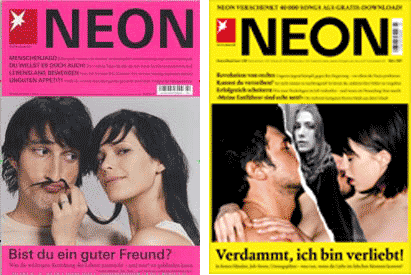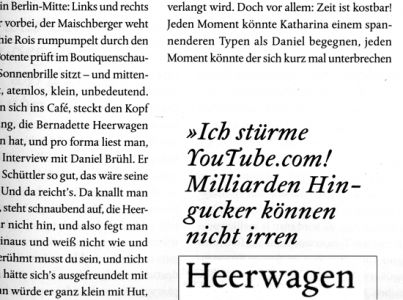
NEON verabschiedet sich von Univers
Das Blatt ist noch keine drei Jahre am Markt und gönnt sich schon eine neues Gesicht. Der Titelschriftzug hat sich in den Proportionen den Kapitälchen genähert, was ich gar nicht schlecht finde. Die Univers ist verschwunden für eine nette Antiqua, die ich leider nicht kenne. Schade um die Univers. Thats life.
der NEON-schriftzug schaut besser aus als vorher.
die positionierung des EAN-codes find ich allerdings
zweifelhaft ...
ich mache morgen mal einen bildschirmschuss. hab die neon gerade nicht im Büro. ist aber nicht die dolly.
Ja, der Schriftzug ist griffiger, besser als vorher, obwohl mir auf diesem 72lpi Shot das abschliessende "N" zu sehr am kreisrunden "O" klebt.
Zur kontrastierenden Serif kann man sich natürlich erst äussern, wenn man das Mag in den Händen hält.
wie versprochen hier eine größere Ansicht.
Ich hoffe, dass man was erkennt.
Times istes aber nicht :-)
Eine Garamond? Aber welche?
Charakteristisch ist das ›g‹ der Aufrechten, mit der großen Punze und dem sehr kurzen Ohr. Bei der Kursiven fallen ›Y‹- und ›T‹-Majuskel auf – so ähnlich zeigt sich die AdobeGaramond in der Schwungschrift-Variante …
florijn: adobe garamond - aber nicht genau gleich? im ersten moment dachte ich auch an diese schrift (auch wegen Y und T kursiv), kann es aber momentan nicht kontrollieren (mein wlan spinnt und ladet nur gewisse seiten).
Thierry: Jetzt wollte ich es wissen – aber … die AdobeGaramond war doch einigermaßen Quatsch.
Ich wusste jedoch, dass ich so ähnliche Swash-Majuskeln schon auf meinem Bildschirm hatte … die AdobeCaslon hatte ich gemeint! Aber auch die ist es nicht.
[bild: links Garamond MediumItalicCaption (teilweise mit Swash-Alternativen / Medium; rechts Caslon Semibold Italic / Semibold]
Je länger ich dieses (Mini-)Bild betrachte, umso mehr gefällt mir die schöne Unbekannte. In jedem Fall eine gute Wahl von Neon!